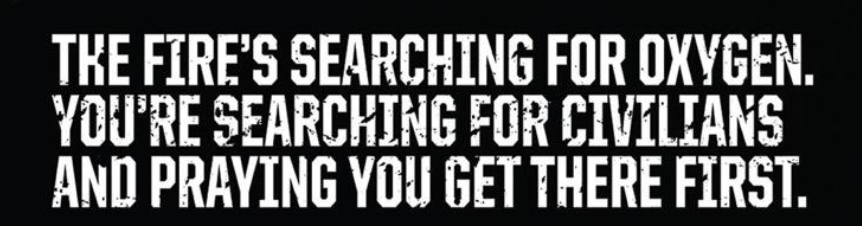
Suche Schrift dieser Werbeanzeige von Mine Safety Appliances
Vielen Dank euch! Gibt es eigentlich einen Begriff für Schriften, die solche Flecken bereits beinhalten? destroyed oder sowas?
Es gab/gibt in CorelDraw (ich habe das Programm schon einige Zeit nicht mehr) die wunderbare Option »Objekt in Behälter platzieren«. Also Schrift in Kurven wandeln, Füllung entfernen, Umriss innen anlegen (je nach Hintergrund auch ohne), gruppieren und dann schlicht ein gemustertes Grafikobjekt mit der o.g. Funktion in den »Schriftbehälter« packen.
Ich habe noch nicht herausgefunden, wie das in Illustrator funktioniert - soll aber gehen.
Ist in Illustrator ganz easy:
Schrift in Pfade umwandeln, zusammengesetzten Pfad erstellen, über Hintergrund platzieren, beides markieren und dann eine Schnittmaske erstellen.